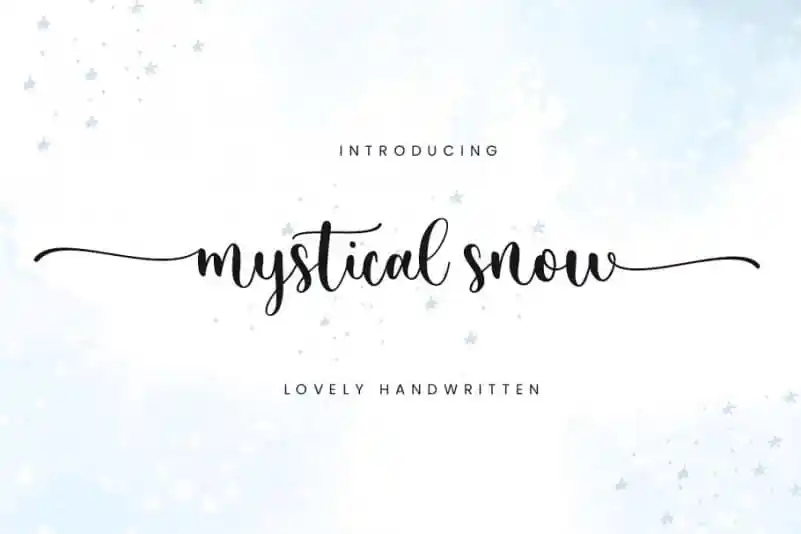
Mystical Snow Calligraphy Font – Fonte Grátis
Mystical Snow Calligraphy Font
Mystical Snow Calligraphy Font é uma bela tipografia escrita à mão que oferece uma variedade incrível de possibilidades para designers, sejam eles profissionais ou entusiastas. Esta elegante fonte foi criada por Sronstudio e compartilhada no 99designs com cuidado meticuloso. Suas nuances delicadas e o aroma fresco da neve branco-acobreada a tornam uma opção perfeita para um amplo leque de projetos, desde embalagens de produtos até postes em redes sociais. Seu design elegante é perfeito para criar designs que vão além do básico, especialmente para aplicações como invitations, estaçãorios, materiais de casamento e mídias sociais. Sua delicadeza única a torna ideal para produtos, desde etiquetas até fotografias. Ela também pode ser usada em design gráfico especial ou qualquer outro projeto que busque dar um toque único. Assim, Mystical Snow Calligraphy Font é uma fonte perfeita para quem está buscando algo mais do que apenas uma tipografia padrão. Com seu ar de neve mágica e seus traços delicados, esta fonte oferece opções incrivelmente únicas, capazes de transformar qualquer projeto em algo único e envolvente.